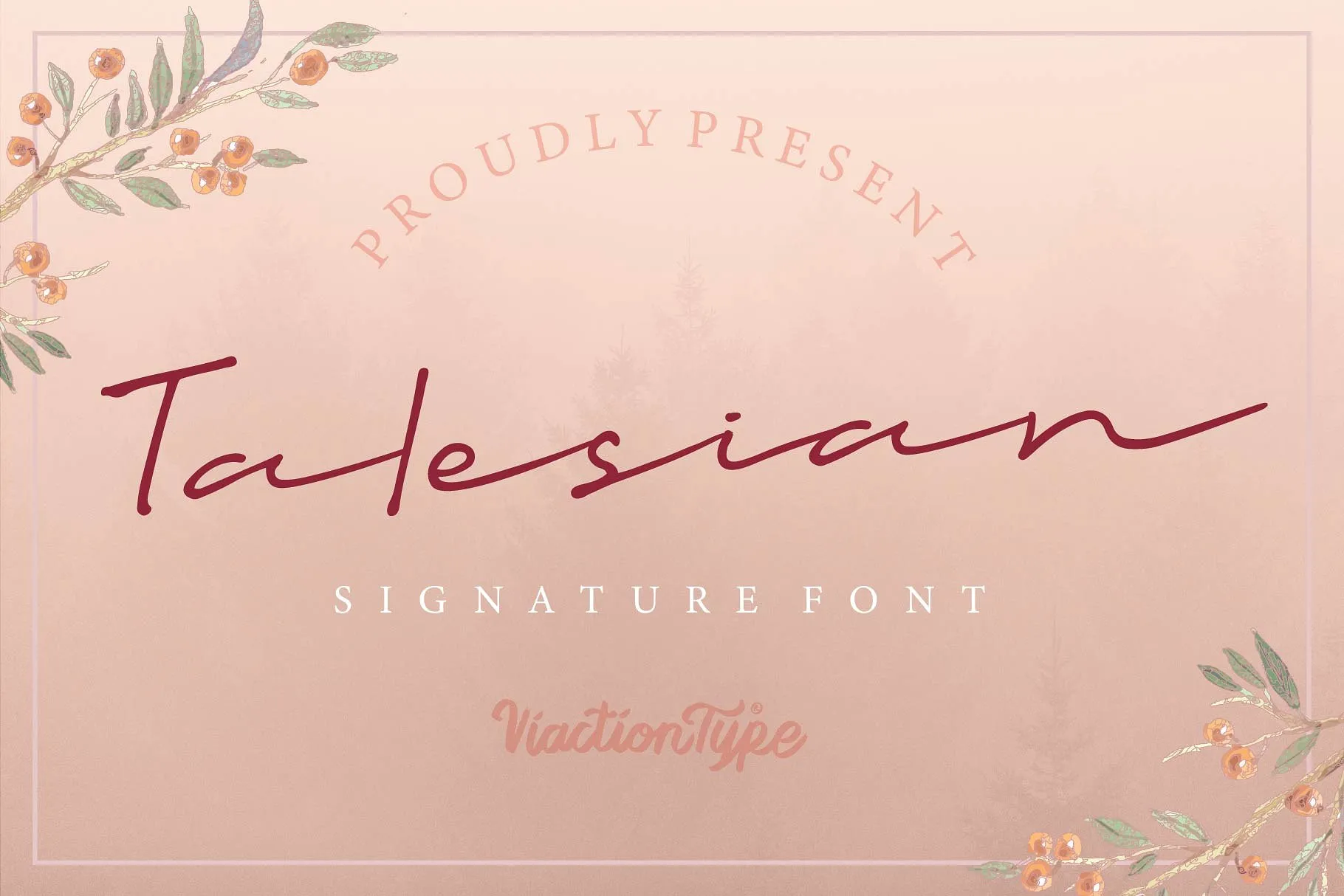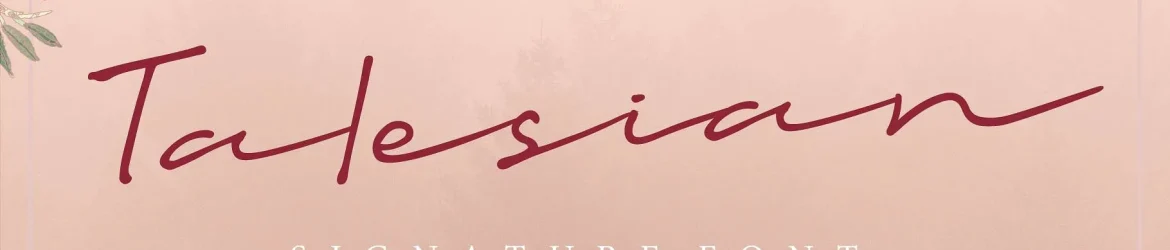
A Talesian Signature Font é uma opção perfeita para designers que buscam uma mão-dupla elegante e natural para seus projetos de design. Escreva ou desenhe com essa fonte, cujo traço fluido se assemelha à autoria humana, proporcionando um toque fresco às suas criações. Este estilo script é perfeito para personalizar mensagens, criar invitações de casamento, desenvolver uma identidade visual única e até mesmo manter conversas dinâmicas em postes de propaganda. Idealmente, a Talesian Signature Font está equipada com todas as características de uma fonte Script OpenType, incluindo ligação automática e suporte multilíngue. Isso significa que você terá um amplo leque de opções para expressar suas mensagens em diferentes formatos e idiomas. Além disso, a Talesian Signature Font se destaca como uma escolha ideal para estilos de marca boutique ou editoriais, projetos fotográficos, postes de propaganda, cartões de business, selos de logo e mais. O designer Viaction Type.Co criou essa fonte única para ajudar os designers na criação de ambientes visuais que são a sua cara. Se você está procurando por uma fonte elegante que ofereça um toque autêntico às suas criações, Talesian Signature é definitivamente um item à vista.